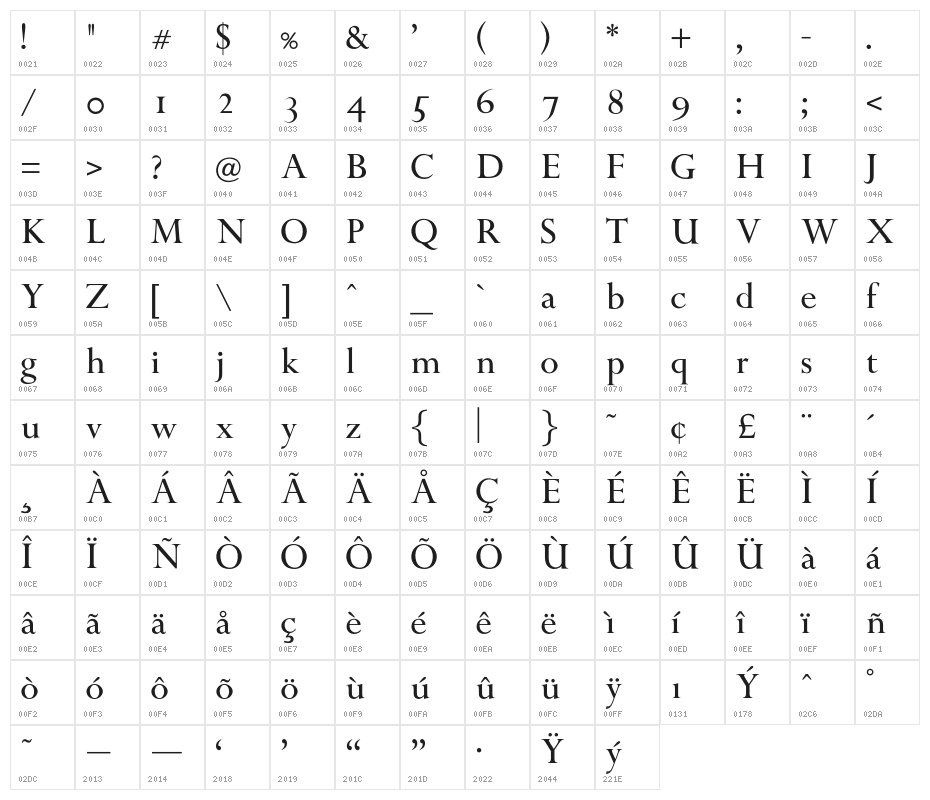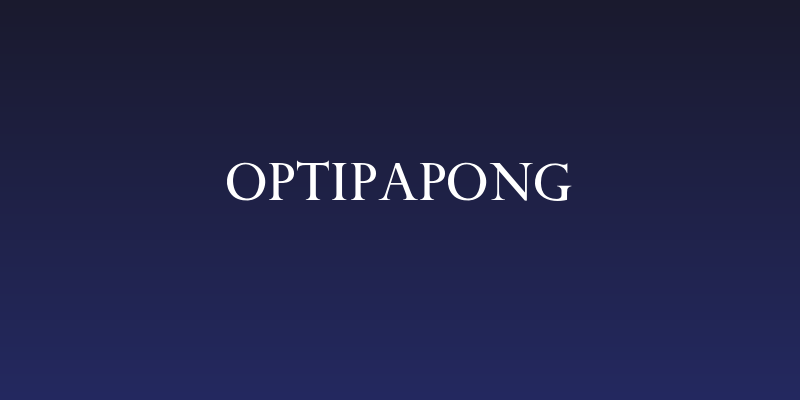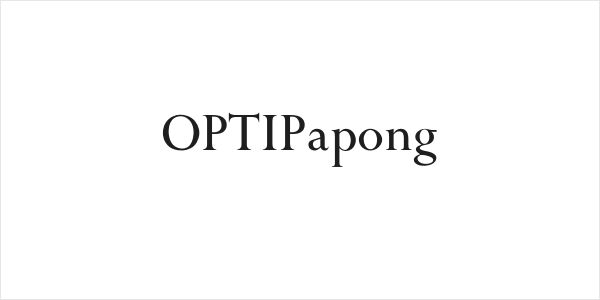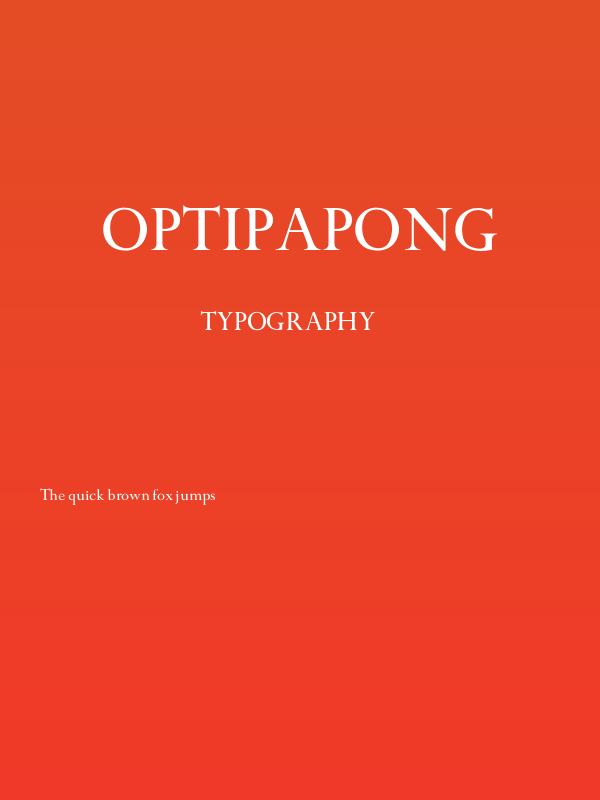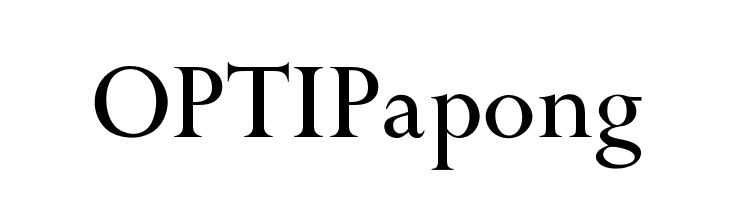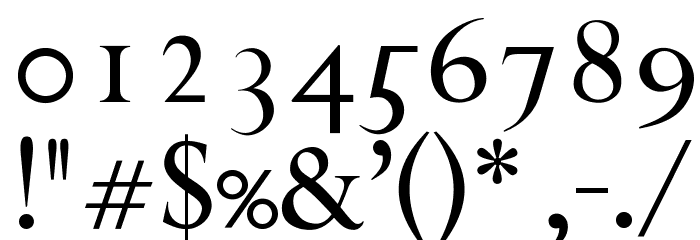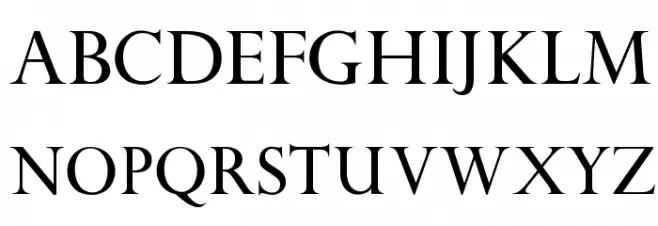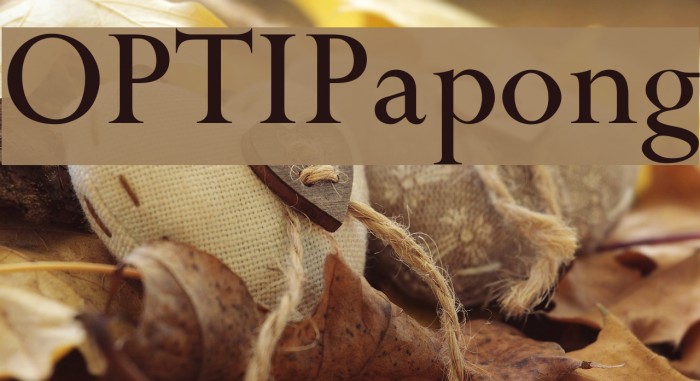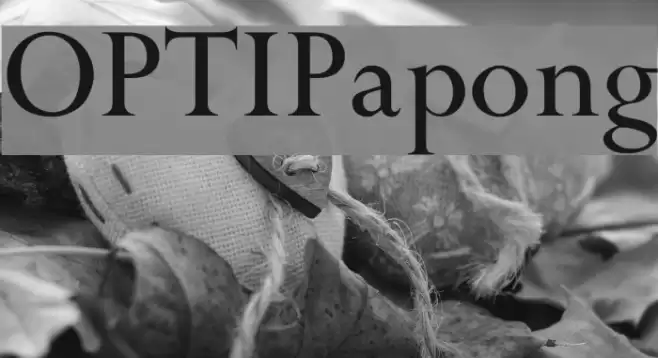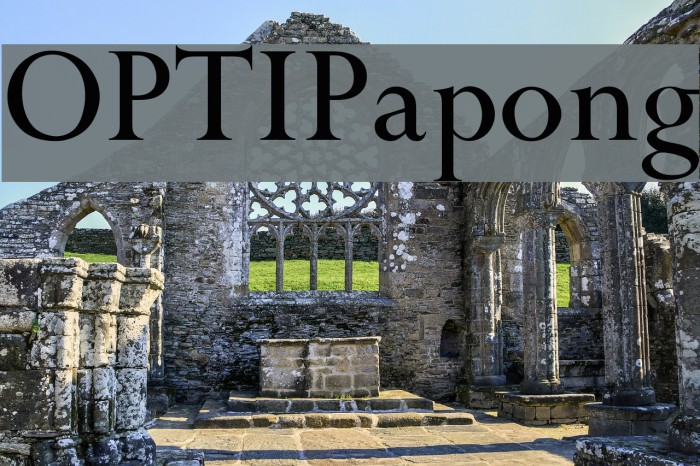
OPTIPapong Font
✎ Serif
| Estilo general | Classic |
| Caso de uso | Headlines, Body text, Logos |
| Proyectos propuestos | Ideal for editorial design, book covers, formal invitations, and branding projects that require a touch of elegance and tradition. |